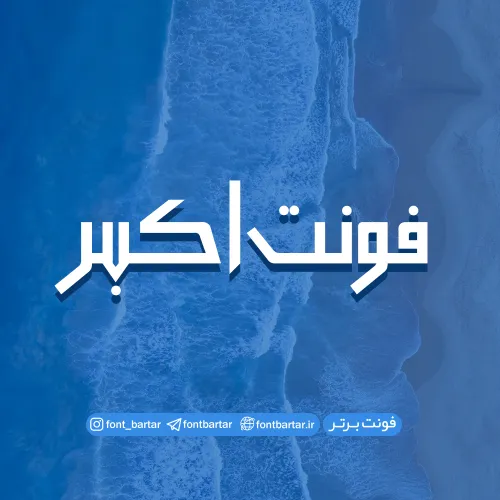
فونت فارسی اکبر
فونت اکبر – Akbar font از جمله فونتهای می باشد که در طراحی آن از سبک خاصی استفاده شده است که باعث شده این فونت جذاب و پرکاربرد شود که در طراحی گرافیک کاربرد بسیار خوبی دارد. این فونت در سه وزن Bold,regular,medium طراحی و استاندارد سازی شده است.فرمت این فونت زیبا TTF است که پس از نصب در سیستم عامل خود می توانید در تمام نرم افزارهای گرافیکی و ویرایش متن از جمله نرم افزار محبوب فتوشاپ ، مجموعه نرم افزاری آفیس و … استفاده کنید.